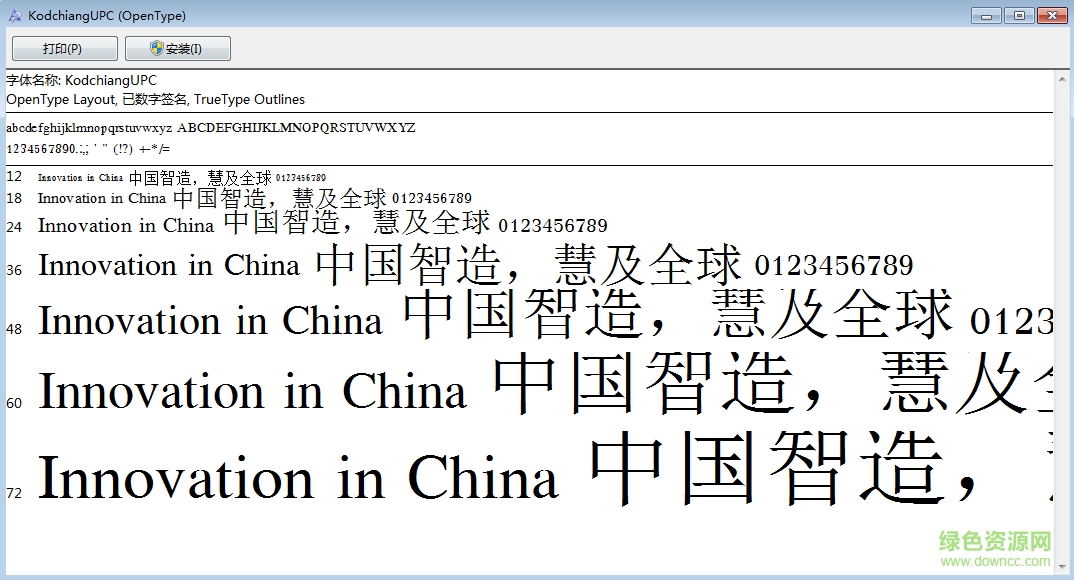
KodchiangUPC是一款字跡干凈流暢的英文字體,精簡(jiǎn)大方的造型讓人很有欣賞美感,喜歡的朋友就來(lái)綠色資源網(wǎng)免費(fèi)下載吧!
KodchiangUPC是一款常見(jiàn)的中英文字體素材,可用于藝術(shù)設(shè)計(jì)、包裝印刷、簽名設(shè)計(jì)、圖形設(shè)計(jì)等領(lǐng)域。